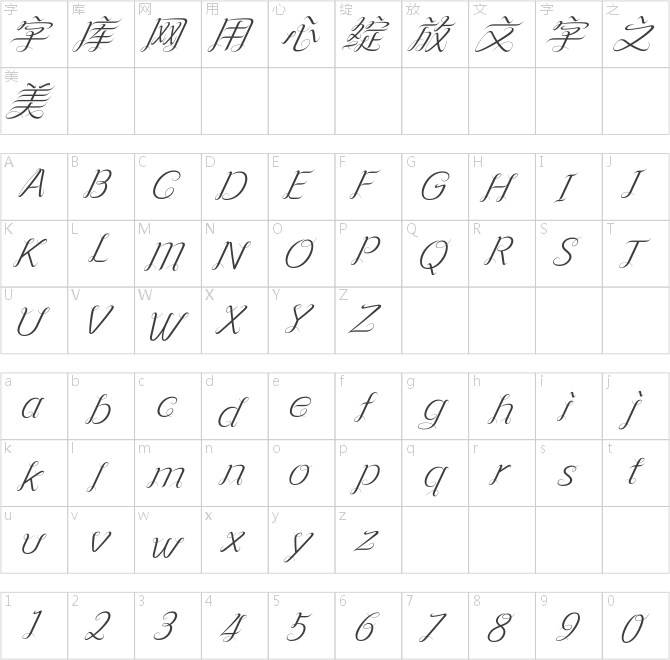
纖舞斜體是一款用“Script”形態演繹的手寫字體,“Script”手寫字體在西方國家非常普遍和流行。本次演繹在中文字體耗時兩年多終于完成。“纖舞斜體”風姿綽約,動人心弦。包含6個字重,是款女性百搭字體,適合高檔品牌,時裝、化妝品,手袋,鞋類,纖體美容,生日卡,情人卡,圣誕卡和各種賀卡,高檔包裝設計也能配合的天衣無縫。
方正纖舞斜體字體FZXianWXTJW字庫是一款讓人賞心悅目、百看不厭的中文字體,適合各類廣告和產品包裝設計應用,字體大小7.28MB,格式為TTF字體,上傳用戶是Amanda白卉,作者/版權方為方正字庫